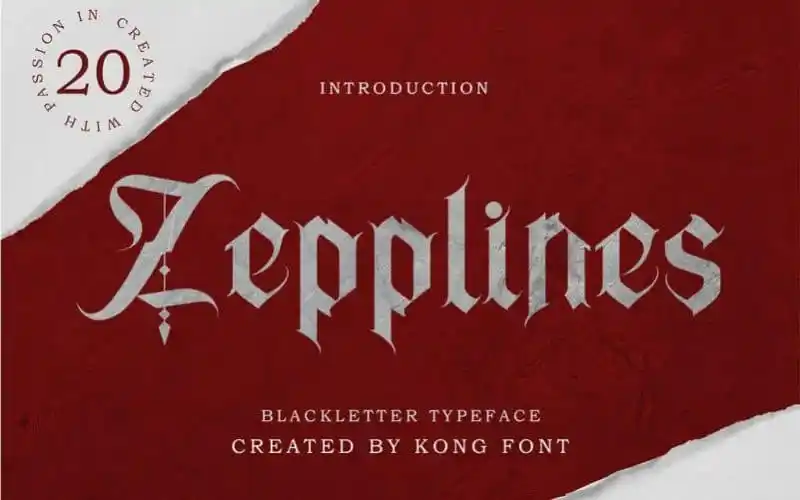
Zepplines Font – Download Grátis
Bem-vindo! Hoje, apresentamos a Zepplines Font, uma tipografia Blackletter Condensada criada pelo designer Hamilton. Inspirada nos estilos retro e minimalistas dos jogos de vídeo primitivos, essa elegante fonte moderna surge como um recurso versátil para design gráfico. Ela é perfeita para criações que exigem um toque vintage ou um tom inconfundível de sofisticação, adequada a uma variedade de propósitos: desde identidades de marca e publicidade moderna até designs góticos e letras em estilo de mão, passando por artes animadas e design editorial. Sua estrutura única permite que você personalize sua criação com uma intensidade poderosa ou um toque discreto, dependendo das suas necessidades específicas. Descubra como Zepplines pode dar vida a qualquer projeto!